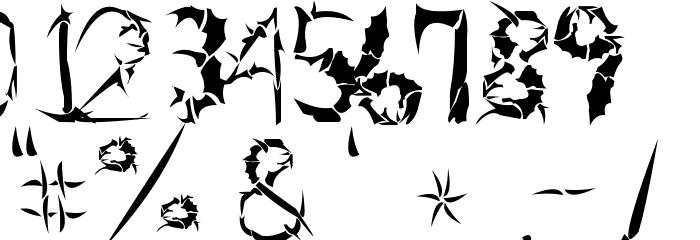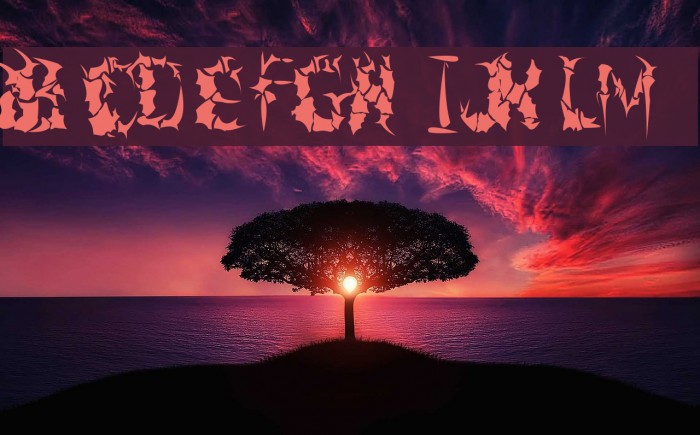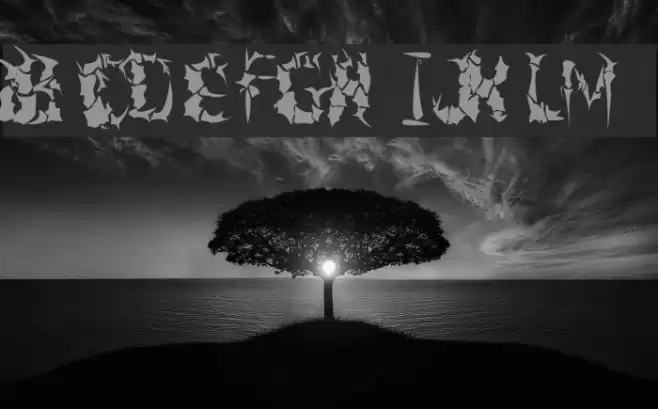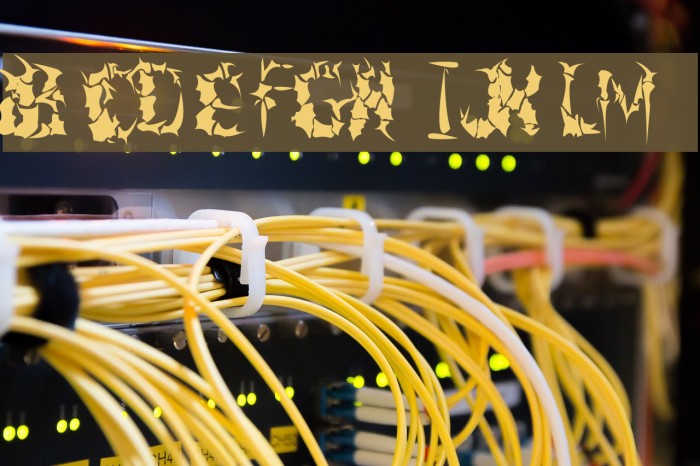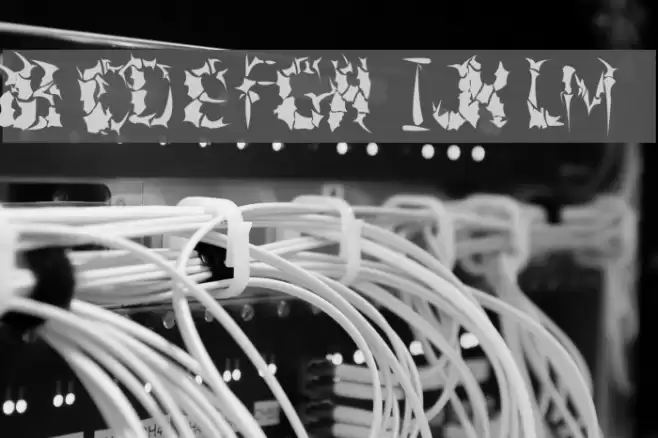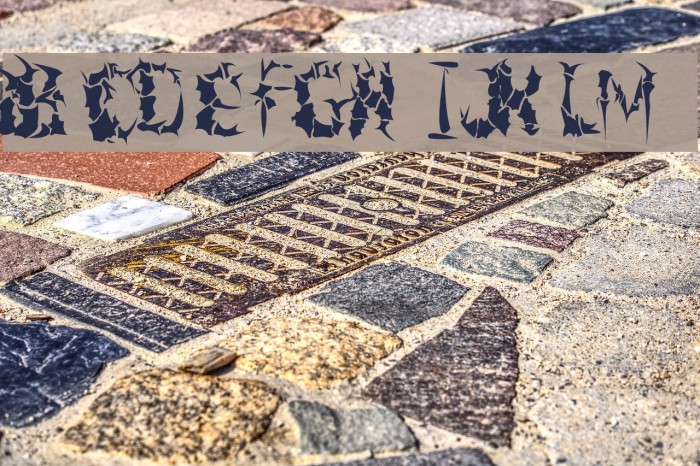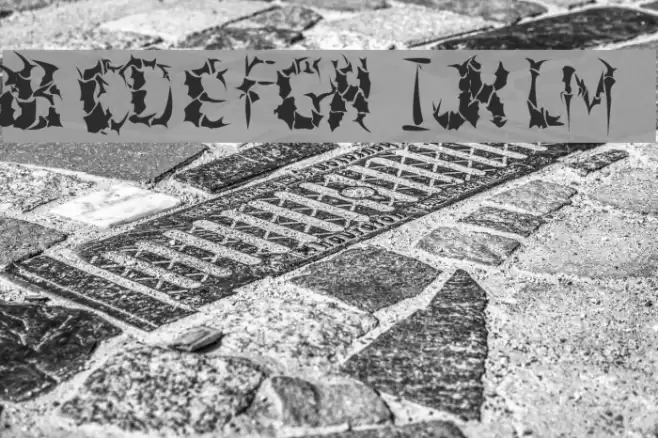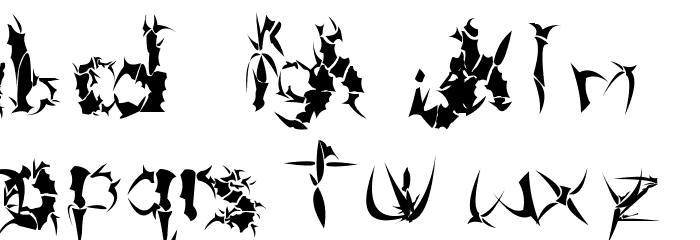
Beneath The Remains Font
✎ Quirky
| Категория | Quirky |
| Область применения | Logos, Headlines |
| Рекомендуемые проекты | Ideal for album covers, posters, or any project needing a bold, artistic statement. |